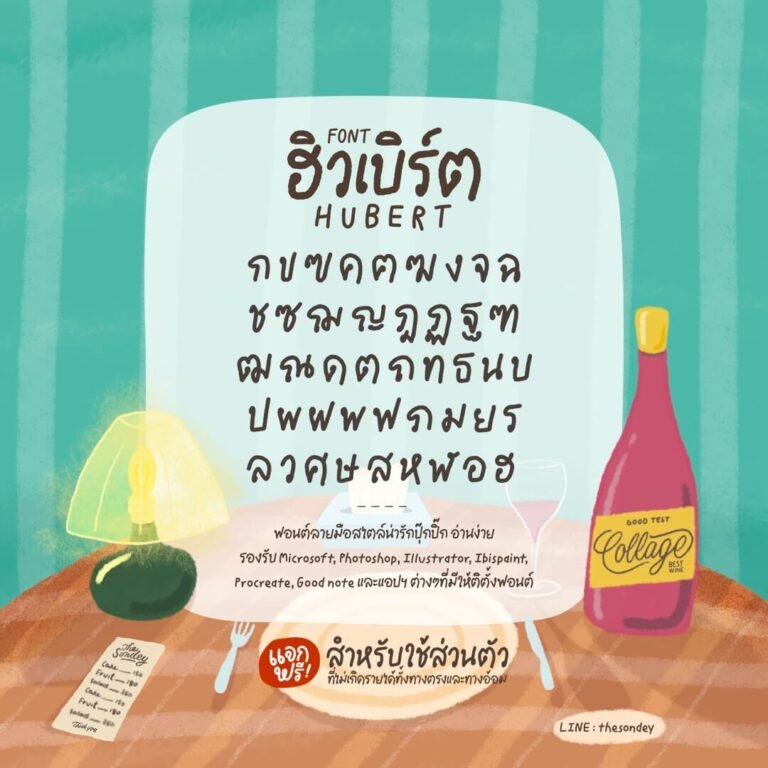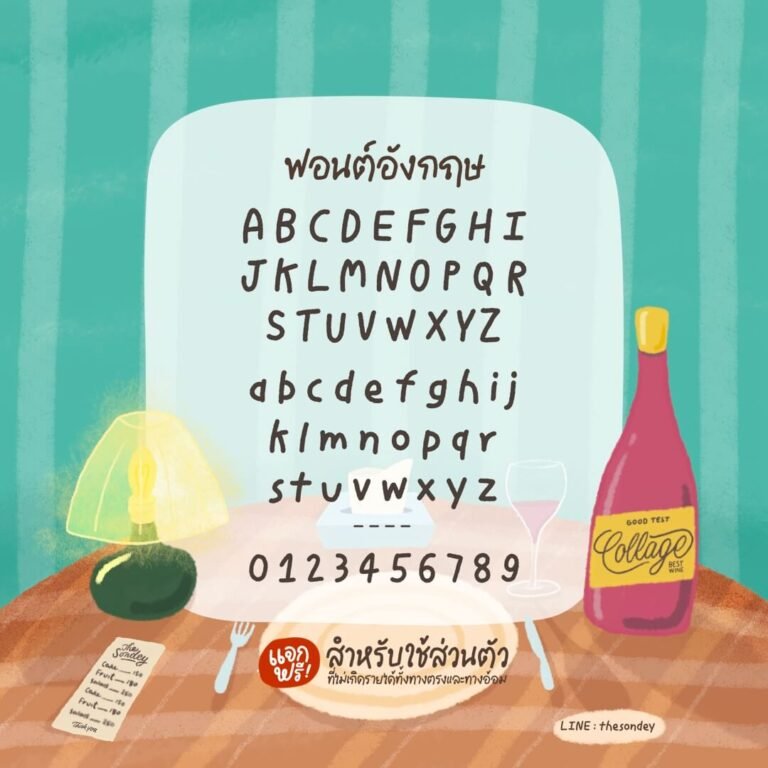
ฮิวเบิร์ต (PG Hubert)
ฟอนต์ลายมือสไตล์น่ารักปุ๊กปิ๊ก อ่านง่าย รองรับ Microsoft, Photoshop, Illustrator, CapCut, ibisPaint, Procreate, Good Note และแอปฯ ต่างๆ ที่มีให้ติดตั้งฟอนต์